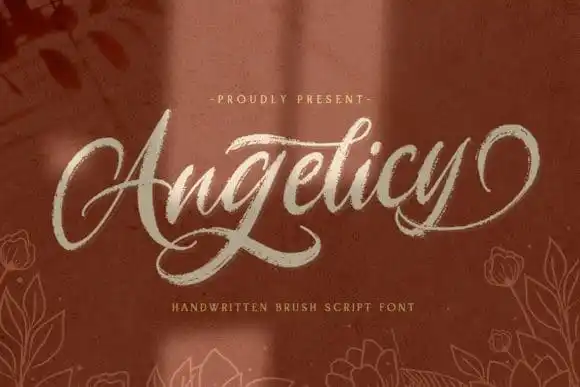
Angelicy Brush Font – Download Grátis
A Angelicy Brush Font é uma elegante tipografia texturizada criada para revolucionar a maneira como você representa seu design contemporâneo. Esta bela fonte, naturalmente feita à mão e com traços suaves soblinhados, não só adiciona um toque especial às suas criações, mas também lhe proporciona uma diversidade incrível de opções para tornar seus projetos ainda mais atrativos. Seu design limpo e um pouco surpreendente a tornam perfeita para uso em logotipos, identidades corporativas, redes sociais e até mesmo naquelas DIY projetos que você deseja fazer com sua própria mão. Seja qual for o seu gosto ou estilo de trabalho, Angelicy Brush Font certamente se encaixa perfeitamente nele. Em um mundo cada vez mais digitalizado, essa fonte traz uma sensação de humanidade e singularidade ao seu design, deixando um sabor inovador em suas criações.